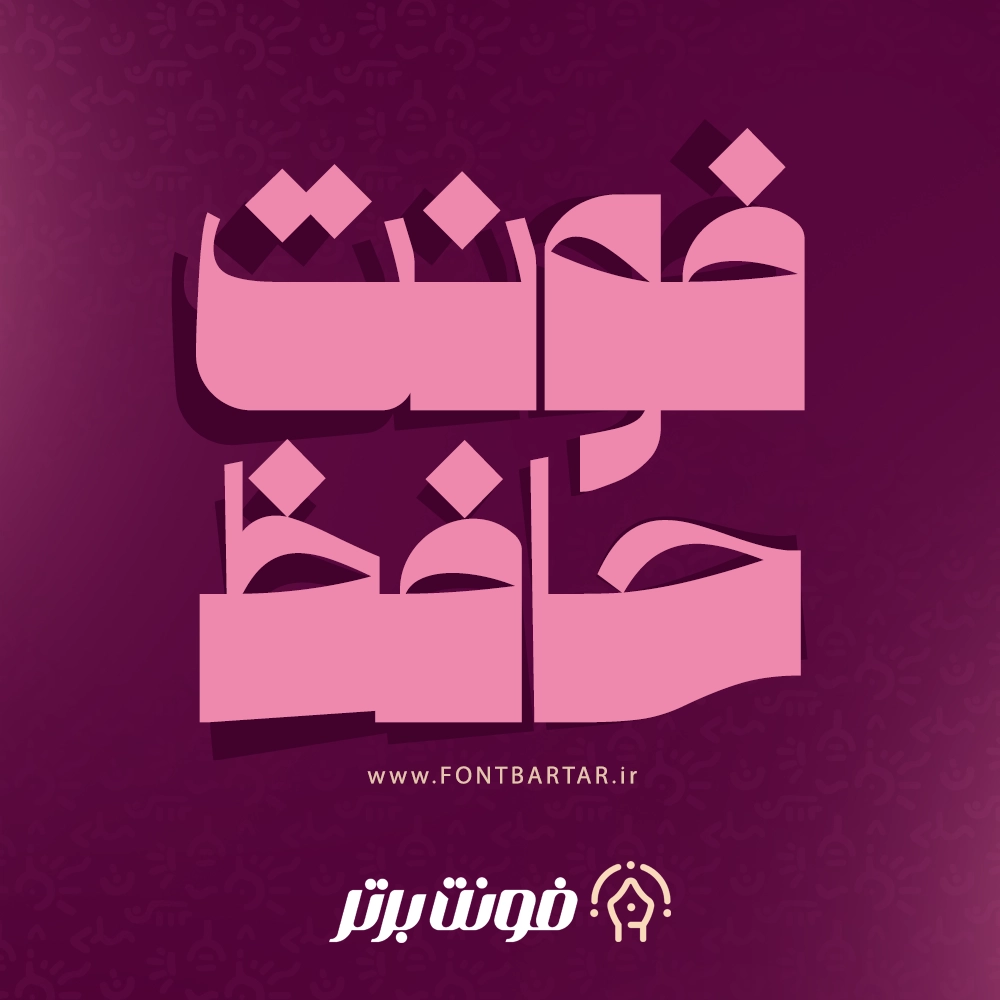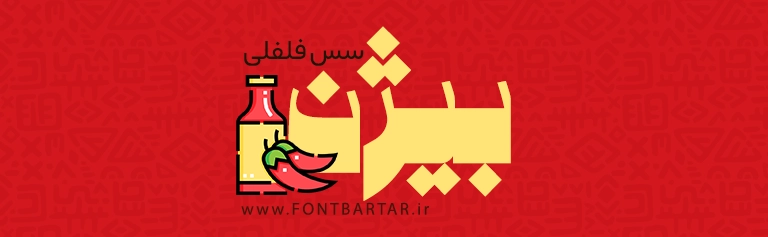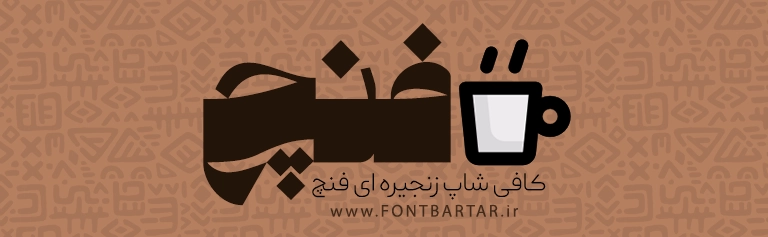
معرفی فونت فارسی حافظ (Hafez Font)
فونت زیبا حافظ یکی از خاصترین و هنریترین فونتهای فارسی است که با الهام از خوشنویسی سنتی و زیبایی اشعار کلاسیک طراحی شده است. این فونت با ساختاری منظم، ضخیم و پرقدرت، برای طراحی پوستر، لوگوتایپ، جلد کتاب، بنر تبلیغاتی و حتی محتوای دیجیتال بسیار مناسب است ، اگر به دنبال یک فونت فارسی خاص و چشمگیر هستید که در عین اصالت، حس مدرن و گرافیکی داشته باشد، فونت زیبا فارسی حافظ انتخابی بینظیر است.
ویژگی های بهترین فونت زیبا حافظ
- 🖋️ طراحی منحصربهفرد با الهام از خطوط سنتی ایرانی
- 🎭 مناسب برای طراحی لوگو، پوستر، جلد کتاب و کارت ویزیت
- 🔤 حروف با ضخامت متعادل و ساختار قدرتمند برای تایپوگرافی
کاربرد های فونت فونت زیبا جدید حافظ
فونت حافظ ترکیبی از زیبایی، اصالت و قدرت بصری است. همین ویژگیها باعث شده تا در بین طراحان ایرانی به یکی از محبوبترین فونت های فارسی تبدیل شود، از این فونت میتوانید در پروژههای زیر استفاده کنید:
- فونت زیبا دانلود طراحی لوگوتایپ با حس کلاسیک و لوکس
- طراحی پوستر و کاور برای موسیقی، فیلم یا کتاب
- ساخت کارت دعوت، بنر مذهبی و فرهنگی
- طراحی صفحات گرافیکی شبکههای اجتماعی
- تایپوگرافیهای شاعرانه و دیزاین سنتی
چرا دانلود فونت زیبا انتخاب طراحان حرفهای است؟
فونت جدید حافظ با الهام از اشعار جاودانهی «حافظ شیرازی» طراحی شده و ترکیبی از زیبایی ادبی، اصالت ایرانی و جذابیت بصری مدرن را ارائه میدهد، این فونت در هر نوع طراحی، حس شاعرانه، فرهنگی و معنوی ایجاد میکند و برای برندهایی که به دنبال هویت ایرانی هستند، بهترین گزینه است.
۱. فونت حافظ برای چه نوع طراحیهایی مناسب است؟
فونت حافظ برای طراحیهای فرهنگی، مذهبی، هنری و تایپوگرافیهای خاص ایدهآل است.